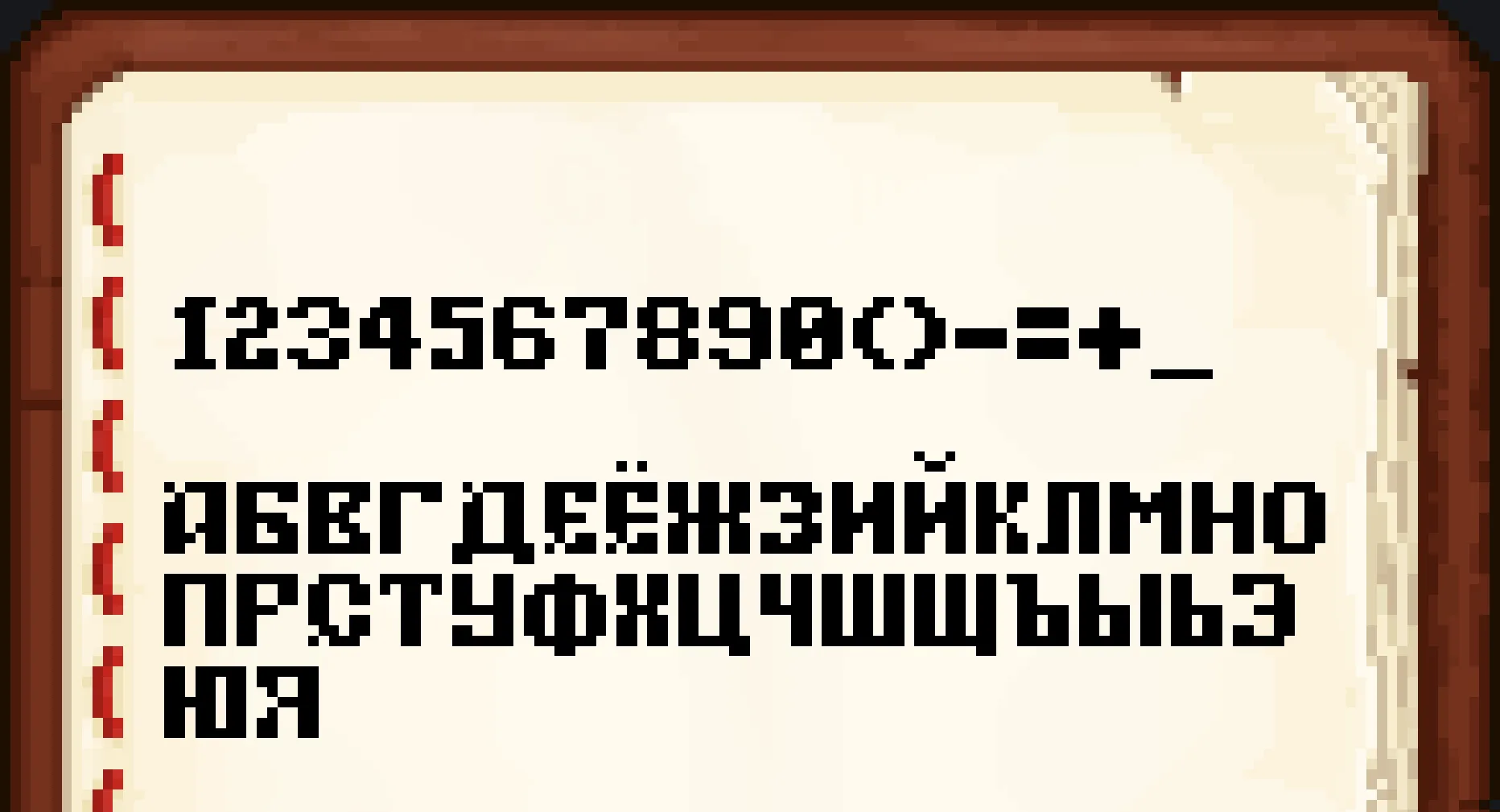
Slavic Fantasy Font
Шрифт в славянском стиле для Minecraft, идеально подходящий для средневековых и фэнтезийных модпаков.
Этот ресурспак изменяет шрифт в игре, придавая ему вид в стиле славянской письменности, вдохновлённой Minecraft. Он отлично вписывается в атмосферу средневековых или фэнтезийных модпаков, добавляя визуальную аутентичность. Шрифт сохраняет читаемость и совместим с указанными версиями Minecraft, не влияя на производительность.